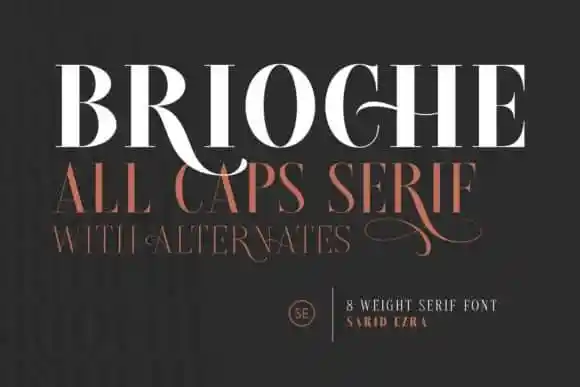
Brioche Serif Font – Download Grátis
A Brioche Serif Font é uma fonte romana com ligação criada pela saridezra através do site 99designs. Inspirada nas serifas clássicas e no luxo tipográfico, essa fonte moderna e sofisticada é perfeita para projetos exigentes. Suavemente delicada, ela combina elegância com uma delicadeza única que permite criar texturas únicas e interessantes. A Brioche é ideal para aqueles buscando um tom mais suave em seus projetos, seja para publicidade ou para criar artigos de design digital. Sua versatilidade faz dela uma opção ótima para qualquer projeto criativo em que você busque estilos sutis e sofisticados. Adicione a sua lista de ferramentas gráficas e observe como ela destaca seus projetos!